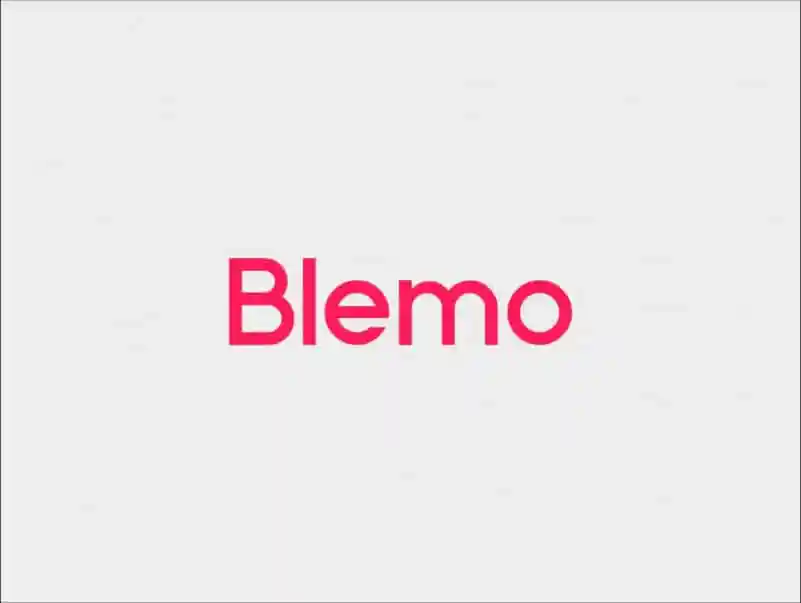
Blemo Sans Serif é uma nova adição ao vasto universo das fuentes sem serif. Conhecida por sua rigidez geométrica, esta fonte mantém fielmente a essência básica do design geométrico, mesmo quando enfrenta o desafio da contraste de traços em letras redondas. Por exemplo, nas famosas tipografias geométricas convencionais, é comum que os princípios básicos de geometria percam alguma relevância por causa da diferença entre os traços de letras redondas. Blemo, uma família de fuentes sem serif, supera essa barreira ao preservar esses princípios geométricos, mesmo quando confrontada com o contraste dos traços em suas letras. Desenvolvida e compartilhada pela Artsigma Design, a Blemo oferece um toque de originalidade à comunidade das fuentes sem serif. Agradeça por adquirir esta fonte única; ela é uma escolha inteligente para quem busca uma tipografia moderna e confiante que expressa precisão e simplicidade.